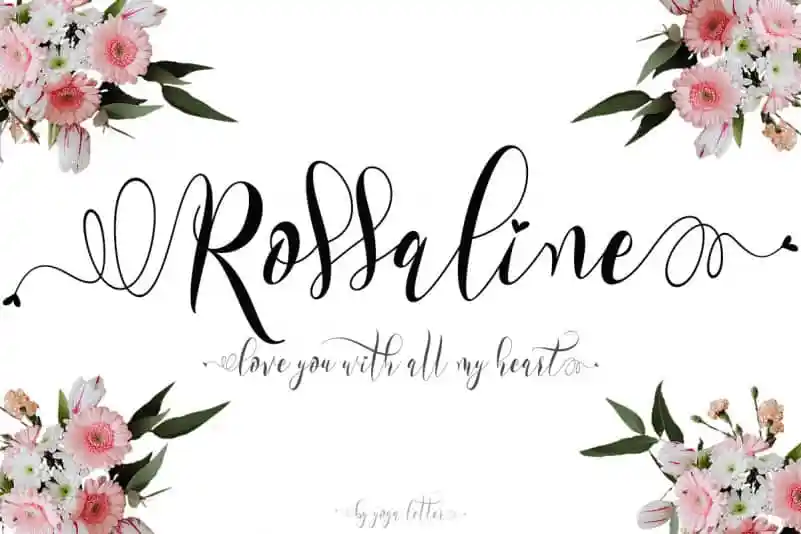
Rossaline Calligraphy Font – Download Grátis
A Rosaline Calligraphy Font é uma escolha perfeita para qualquer designer buscando dar um toque especial a suas criações digitais. Este font foi meticulosamente criado por Yoga Letter, evidenciando sua beleza e qualidade excepcionais. Ideal tanto para ilustrar seus produtos ou apresentar seu negócio, quanto para criar citações, convites de casamento, logotipos e até mesmo publicações em redes sociais, a Rosaline proporciona um toque elegante que enriquece qualquer projeto. Além disso, sua simplicidade permite ao designer expressar seus sentimentos mais profundos ou celebrar momentos memoráveis, tornando-a uma fonte versátil e atraente para diversos usos. Com seu design cuidadosamente elaborado, Rosaline é definitivamente um recurso gráfico que não deve ser esquecido.